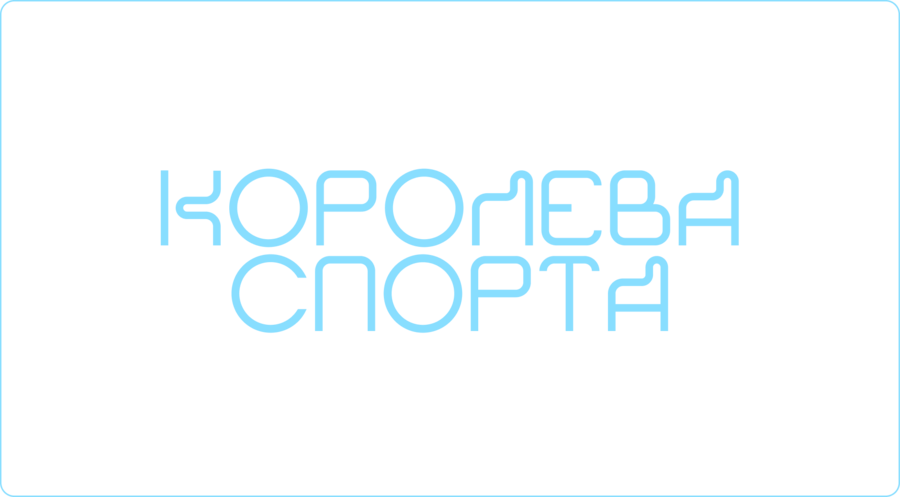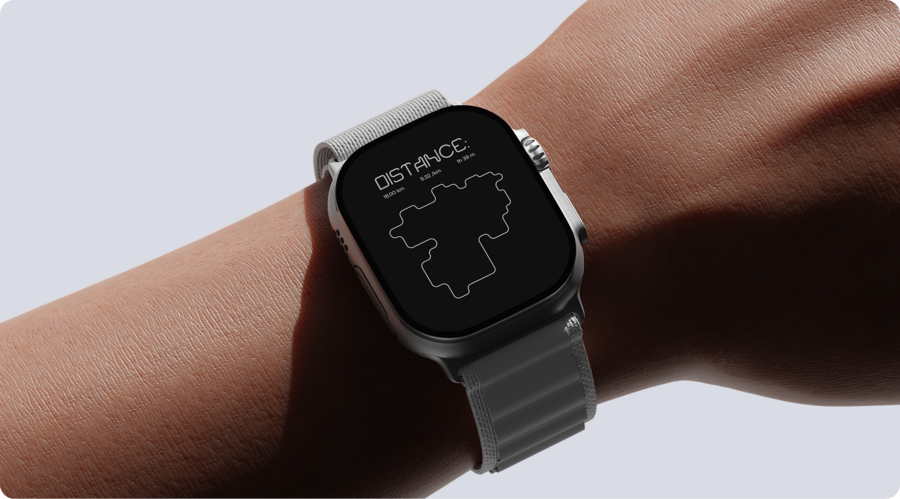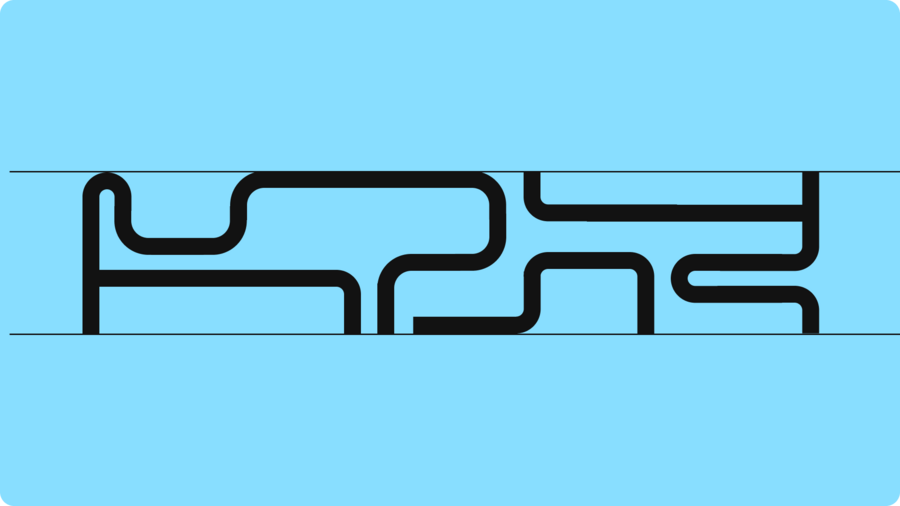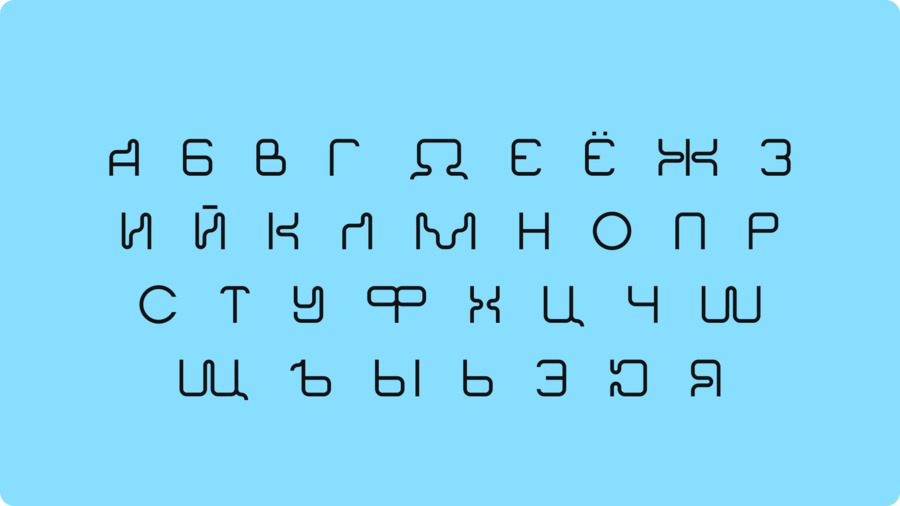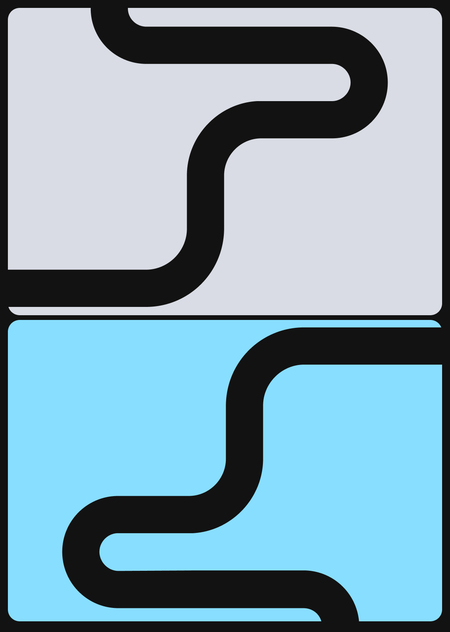
Шрифт основан на базе траекторий беговых маршрутов легкоатлетов на стадионе, городских дистанцях и записей геотрекера
Прямые элементы букв передают движение вперёд, а скругления работают как повороты дорожки и смена направления на дистанции